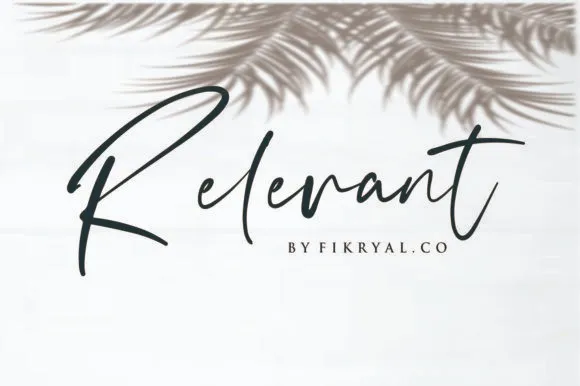
Relevant Script Font – Download Grátis
Aqui está uma descrição em português do Brasil para a página de download da fonte ‘Relevant Script Font’: Estamos certamente felizes por você ter prestado atenção à Relevant Font, uma elegante e moderna tipografia de calligrafia que incorpora um toque de estilo de escrita manual. A Relevant Script é perfeita para dar ao seu design um toque autêntico de trabalho artesanal. Esta tipografia contemporânea e clássica faz dela uma fonte versátil e ideal para vários tipos de projetos. Seja em branding, decoração de casa ou embalagens de produto – Relevant Script está perfeitamente adaptada a qualquer biblioteca de fontes de alta qualidade! Além disso, é uma opção incrível como um texto estilizado para ser aplicado sobre qualquer imagem de fundo. Perfect para qualquer projeto onde você precisa de textos elegantes e profissionais. Relevante Font é certamente uma escolha inteligente, especialmente se sua produção incluir tanto design gráfico quanto marketing e branding. A estética sofisticada desta fonte torna-a ideal para criar uma identidade visual única e atraente, seja por meio de logotipos, slogans ou qualquer outra forma de comunicação visível em sua marca.